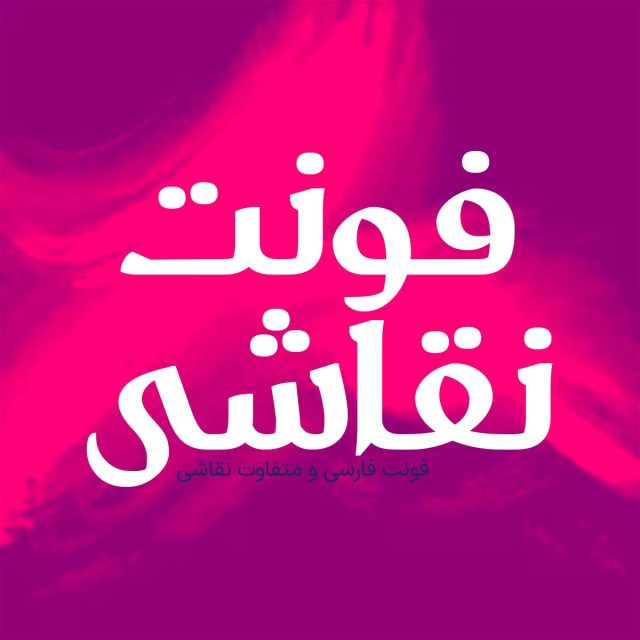
فونت فارسی نقاشی Naghashi Font
فونت فارسی نقاشی یک فونت تک وزن با کاربرد طراحی لوگوتایپ و طراحی های مختلف همچون کتاب و تولید محتوای متن های کوتاه و عناوین می…
فونت فارسی نقاشی یک فونت تک وزن با کاربرد طراحی لوگوتایپ و طراحی های مختلف همچون کتاب و تولید محتوای متن های کوتاه و عناوین می باشد. این فونت با ساختار حروف خود مناسب استفاده در لوگوهای نوشتاری می باشد. همچنین از این فونت در طراحی تابلوهای چلنیوم هم به دلیل ساختار منحصر به فردش می توانید استفاده کنید. در ادامه برای شما نمونه تایپ های این محصول حرفه ای رو آماده کردیم که میتونید مشاهده کنید.